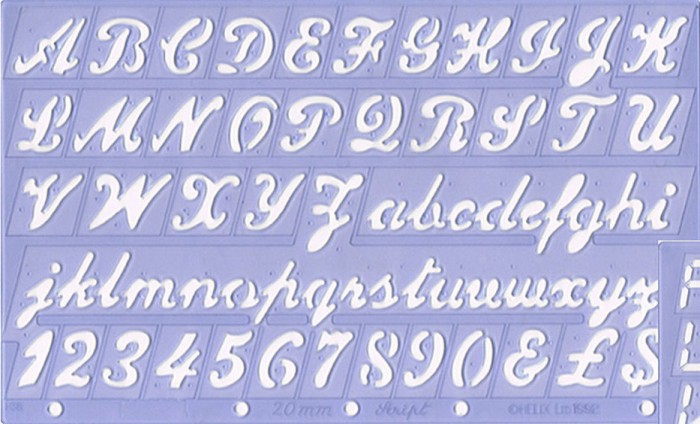
Über die automatischen Suchen im Internet bin ich nicht weitergekommen. Kann mir hier jemand helfen.
Ich suche die Schrift, die man auf dem Bild im Anhang sehen kann.
Und wenn du die automatischen Erkennungsprogramme nujtzen willst, brauchst du die Buchstabebn auch vereinzelt, also zuerst in einer Buildbearbeitung das Schriftbild bei verbundenen Schriften so aufarbeiten, sonst kann die Automatik keine Buchstaben erkennen oder mit anderen der Datenbank auf Ähnlichkeit vergleichen:
Allerdings ergibt das zwar ein paar entfernt ähnliche, aber aus dem schon genannten Grund nicht diese.Daher mein Tip nur als generellen Hinweis zu den Schrifterkennern.
Habe lange gerätselt, warum mir die Schrift so vertraut vorkommt. Inzwischen bin ich mir sicher, dass ich sie in meiner Kindheit praktisch auf jedem Pokal und jedem Vereinsartikel gesehen habe.
Vorhin habe ich noch gelernt, dass man in der Zeit vor der Lasergravur (neben Freihand) auch Schablonen benutzt hat. Ich würde sagen, dass ich die Schablone für eine fast identische Schrift gefunden habe. Leider noch nicht als TTF. :(
Mein persönliches Fazit:
Ich denke, dass es sich um einen ausgestorbenen fräsoptimierten Font handelt, den man vielleicht noch auf hübschen schrägen Messingplättchen findet, aber nicht mehr digital. Grund könnte sein, dass man heute viel flexibler fräsen kann und die ästhetischen Nachteile der alten Schablonen nicht mehr in Kauf nehmen muss.